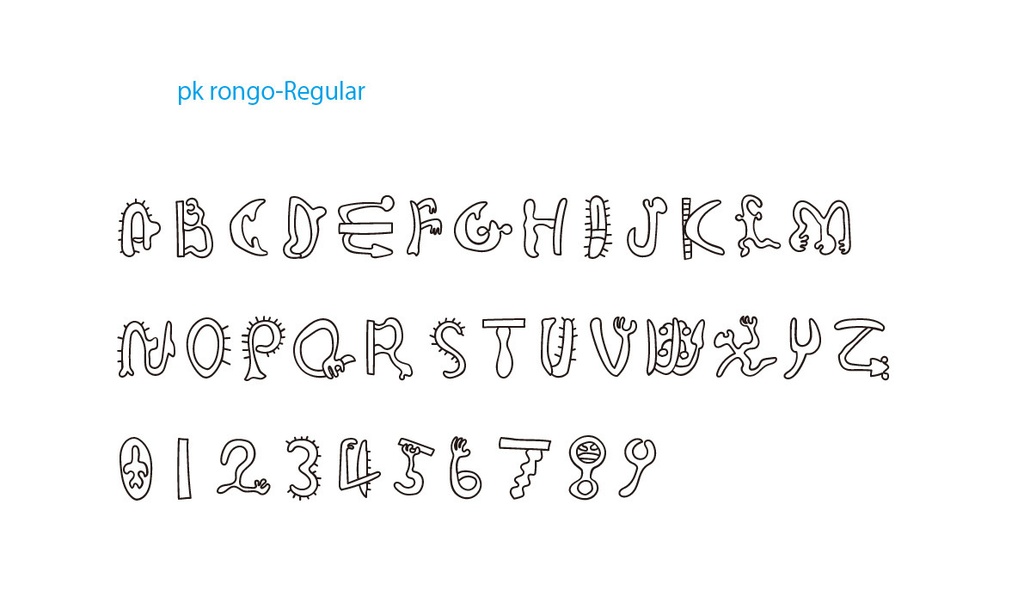
デジタルコンテンツ ロンゴロンゴ風フォント
イースター島で発見された未解読文字ロンゴロンゴをイメージして作った英文字アルファベットと数字のフォントです。 ロンゴロンゴの文字そのものを流用したもの(I,M,Nなど)、ロンゴロンゴの文字をもとにアルファベットや数字に似せて改変したものからなりたちます。 【収録文字】 英大文字 ABCDEFGHIJKLMNOPQRSTUVWXYZ 数字 0123456789 【データ内容・使用方法】 zipファイルを解凍してください。 OTFファイル pkrongo-Regular.otf JPGファイル(文字表示の見本) font-sample.jpg テキストファイル readme.txt が収録されています。 pkrongo-Regular.otf をインストールしてください。 【購入の際の注意点】 商用利用OKです。 使用した場合、ご一報いただけるとうれしいです。Twitterなどで紹介します。 フォントファイルの改変・再配布は禁止です。